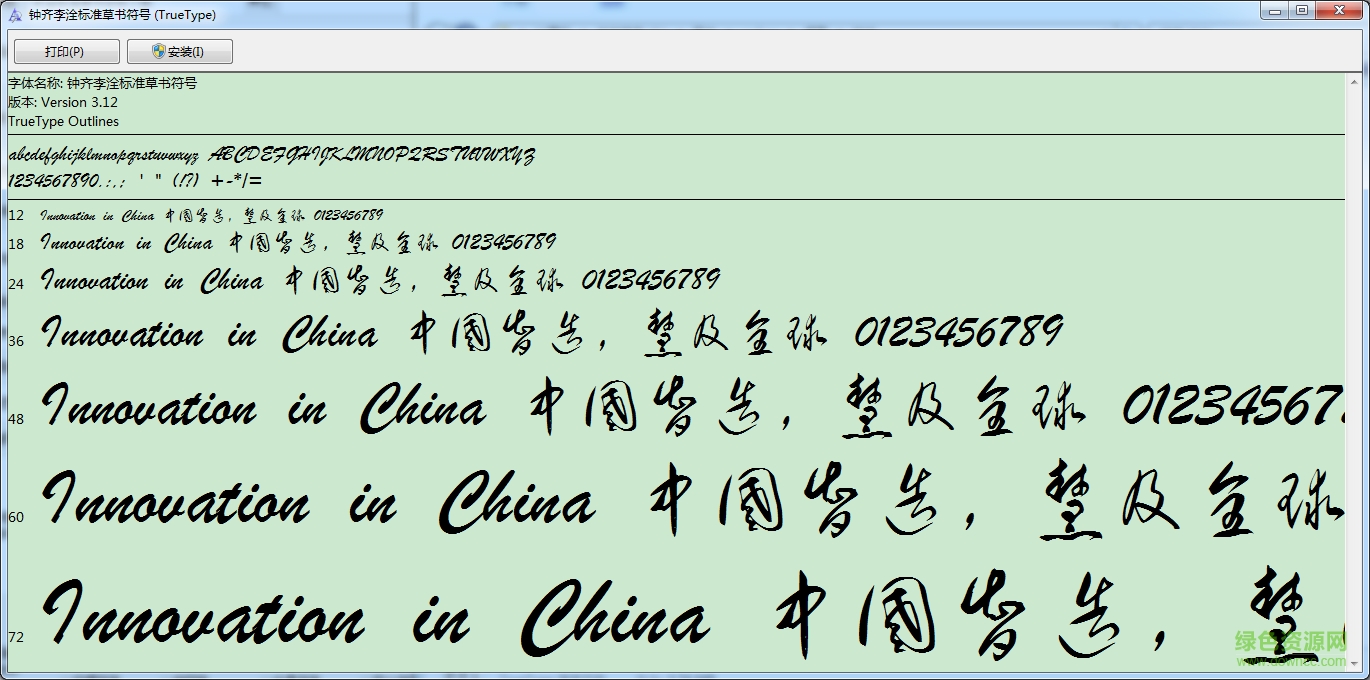
liquan cao字體就是鐘齊李洤標準草書符號,結體舒展,筆畫具有張力,線條連帶流暢,略有些狂亂,但是整體非常優(yōu)美,需要的朋友快來本站下載吧!
【氣勢貫通】
若用筆滯凝,神情呆板,拘謹不暢,則必無勢可言,貫氣更談不上了,所以書法藝術得勢才能得力,得力才能得氣,得氣才能得神,草書之作全在神馳情縱,得心應手之間寫出精神和氣質來。
【錯綜變化】
草書章法之錯綜變化難以名狀,錯綜者指字之大小錯綜、疏密錯綜、用筆輕重錯綜,欹正錯綜等
【虛實相生】
草書章法理應“虛實相生”。“實”指紙上的點畫,也即有墨的黑處;“虛”指紙上點畫以外的空白,也即無墨的白處。